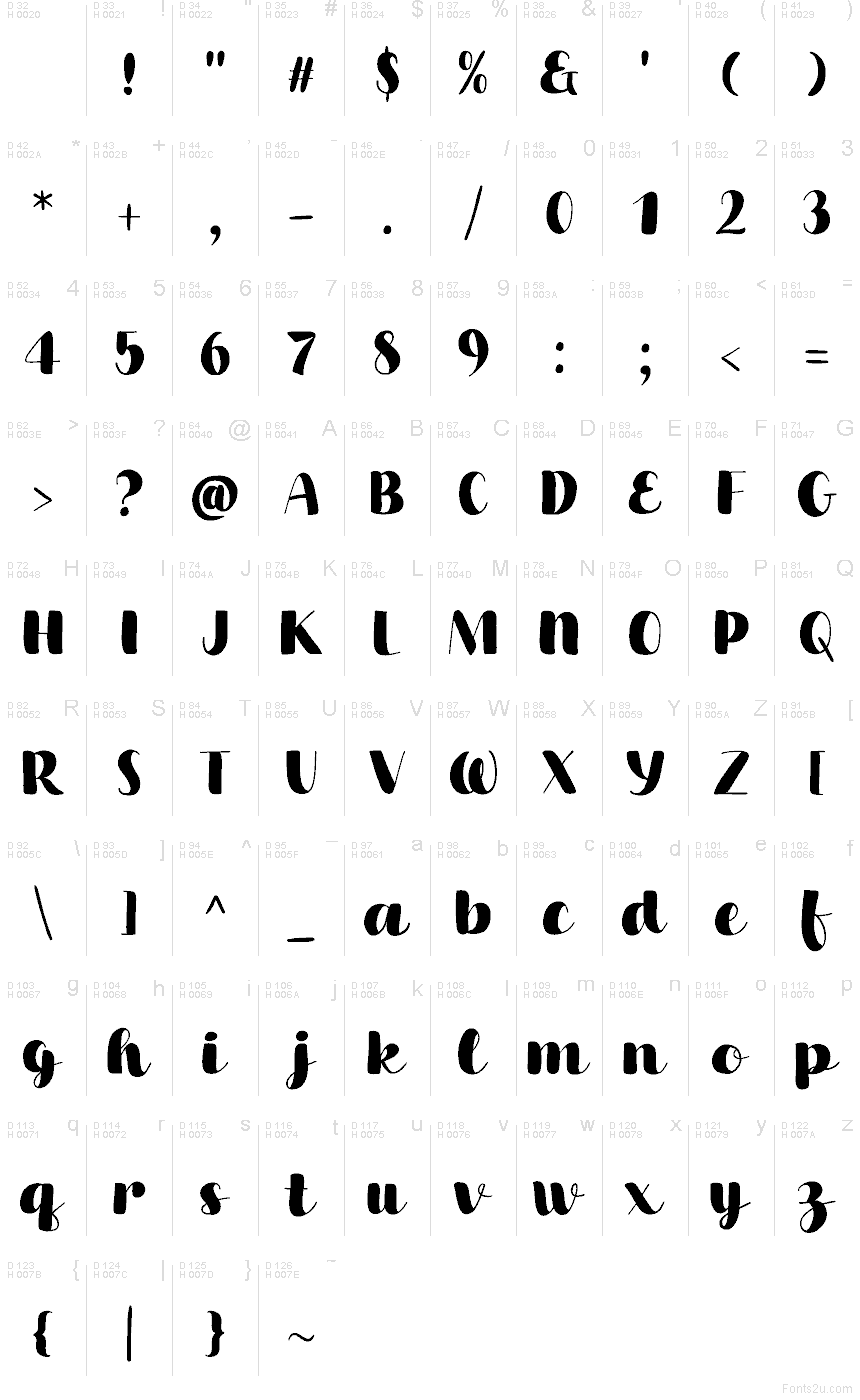
Bubble West від Hello Good Studio - це безкоштовний пензлевий шрифт з округлими, плавними літерами та м’яким рукописним ритмом. Штрихи перетікають у плавні вигини, а поєднані форми надають шрифту дружньої, дещо грайливої енергії, не втрачаючи при цьому своєї структури.
Bubble West чудово підходить для меню кав'ярень, графіки у соціальних мережах, логотипів, карток із цитатами, пакування та коротких заголовків на плакатах, адже його округлий стиль мазків пензля додає невимушеного, особистого характеру. Плавність форм робить його вдалим вибором для акцентів у брендингу, етикеток продуктів та вітальних листівок - там, де рукописний стиль виглядає значно природніше, ніж звичайний декоративний шрифт.
Bubble West